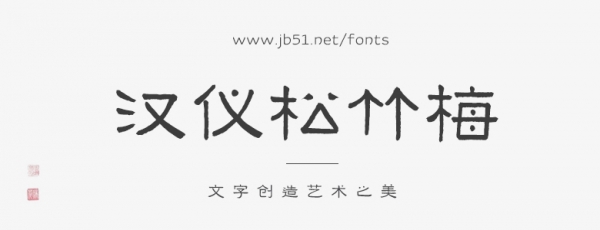
汉仪松竹梅是一款古典隶书风格手写字体。字体以隶书为基本形态框架,引入篆书的用笔方法进行书写,整体纯用中锋笔法,舍弃汉隶中典型的波磔特征,使笔画趋于平直克制,呈现出内敛而稳定的视觉状态。
在笔法处理上,字体汲取传统书法中自然的笔锋变化,强调“化繁为简”的书写观念。线条转折处保留拙朴、含蓄的笔意,让字体兼具书写韵律与沉稳基调,既呈现出气势雄浑的视觉张力,又兼顾现代排版所需的视觉识别性与版面稳定性。
汉仪松竹梅跳脱出传统书法风格,通过结合伊秉绶书法中内敛、凝练的结构特征加以重构,最终形成兼具深厚传统底蕴与独特性的设计风格。
该字体适用于文艺出版、中式视觉系统、文化品牌及具有东方气质的排版场景,通过字体传达清雅含蓄的东方审美与时间沉淀感。